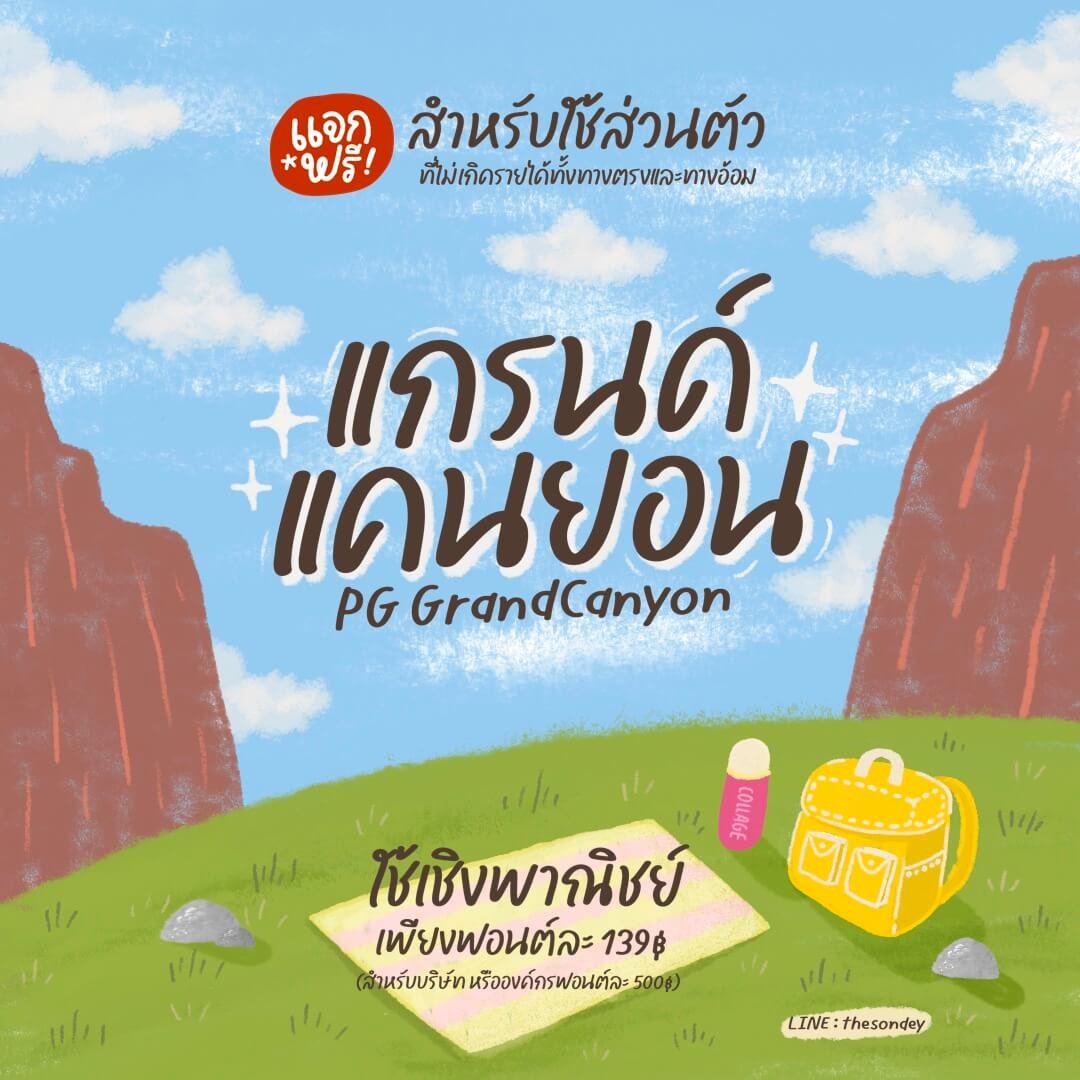
แกรนด์แคนยอน (PG Grandcanyon)
ฟอนต์ลายมือสไตล์น่ารักปุ๊กปิ๊ก อ่านง่าย รองรับ Microsoft, Photoshop, Illustrator, CapCut, ibisPaint, Procreate, Good Note และแอปฯ ต่างๆ ที่มีให้ติดตั้งฟอนต์